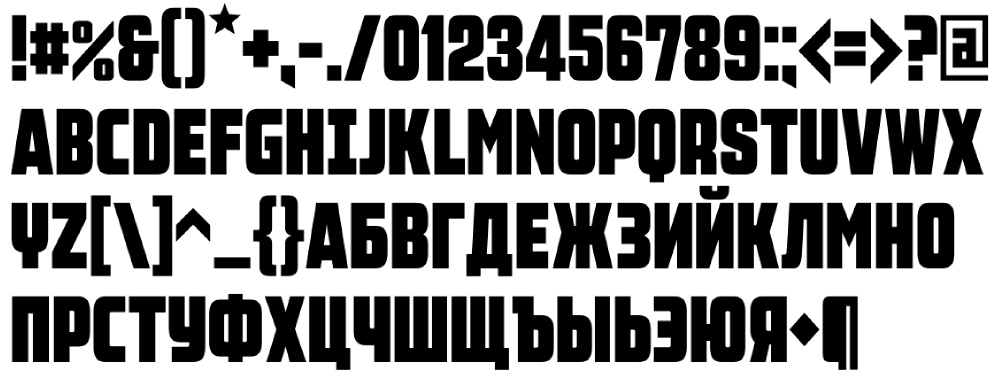
20 новых бесплатных коммерческих шрифтов на 2021 год
Нано-бамбуковое волокно
Нано-бамбуковое волокно футуристический строчный шрифт. Ультрасовременный, минималистичный дизайн обеспечивает отношение, полезное для брендинга и логотипов.
черный
черный — это дисплейный шрифт, созданный на основе квадратной геометрической сетки, обеспечивающей высокий контраст каждой буквы. Nera Heavy доступна бесплатно.
Дирга
Дирга — современный особо жирный шрифт с верхним и нижним регистрами. Его угловатый дизайн футуристичен и напоминает ранние компьютерные шрифты.
Художник
Художник — это шрифт кисти с заглавными буквами, подходящий для дисплеев и Логотипы.
Дженрив Титлинг
Дженрив Титлинг классический шрифт с засечками. Это версия с заглавными буквами, доступная светлым, обычным, жирным шрифтом и курсивом.
Богарт
Богарт — это малоконтрастный шрифт, вдохновленный дизайном с толстым лицом 1920-х годов, который получил статус поп-культуры в хиппи-прессе 1960-х и 1970-х годов. Шрифты Light Italic и Semi Bold бесплатны.
Халани
Халани — это толстый шрифт, который выглядит стильно, но при этом читается.
Малик
Малик — это расклешенный шрифт без засечек, сочетающий классические буквенные формы с современными шрифтами без засечек, что обеспечивает удобочитаемый и удобный дизайн. Malik Book — бесплатная версия.
Пало
Пало обладает плавными конструктивными особенностями, но не чрезмерными Palo Compressed Medium и Palo Wide Light бесплатны.
Хагрид
Хагрид разработан для использования в редакционных и демонстрационных целях, отличается исключительной контрастностью и уникальными деталями. У Хагрида шесть гирь, от монолинейных и более традиционных тонких до выразительных тяжелых. Свободный вес: Обычный, Курсив, Обычный текст и Курсив.
Жало
Жало — современный гротескный шрифт с индивидуальностью — от каллиграфического стиля тонких шрифтов до скульптурных контрастов тяжелых вариантов. Свободные веса: курсив, полужирный курсив, подходящий свет и широкий тонкий.
Фиорина
Фиорина это современное семейство шрифтов с засечками. Гарнитура имеет 18 стилей и четыре веса, что обеспечивает большую гибкость. Text Light и Text Light Italic бесплатны.
Расстояние Антара
Расстояние Антара — еще один скриптовый шрифт. Он тонкий и элегантный, с размеренным чутьем.
Гога
Гога представляет собой современный геометрический шрифт без засечек. Он смешивается равномерно, не отвлекая читателя, но при этом сохраняет богатый и выразительный характер. Gogh Extra Bold и Gogh Extra Bold Italics бесплатны.
Гарбата
Гарбата заимствует свой скелет из гарнитур старого стиля, сохраняя причудливые наклонные формы некоторых букв и добавляя плоскую каллиграфическую кисть.
Гонцеррат
Гонцеррат чистый и структурный шрифт без засечек с 18-ю полнотой, подходящий для заголовков и брендинг.
Mondia
Mondia это современное семейство шрифтов с засечками, вдохновленное переходными и современными шрифтами. Mondia отличается высокой контрастностью символов, что придает ей элегантный вид.
Шрифты Thin и Thin Italic бесплатны.
Фигуристы
Фигуристы — это простой и объемный современный дисплейный шрифт для логотипов, заголовков, брендинга и уличного дизайна.
Амагро
Амагро контрастный шрифт с засечками. Предназначен для заголовков газет, он удобен для плитки, логотипа и брендинга.
Вендура
Вендура элегантный шрифт с засечками в современном стиле. Вдохновленный высококонтрастными шрифтами 18-19 веков, Vendura демонстрирует детали дизайна, которые придают индивидуальность.